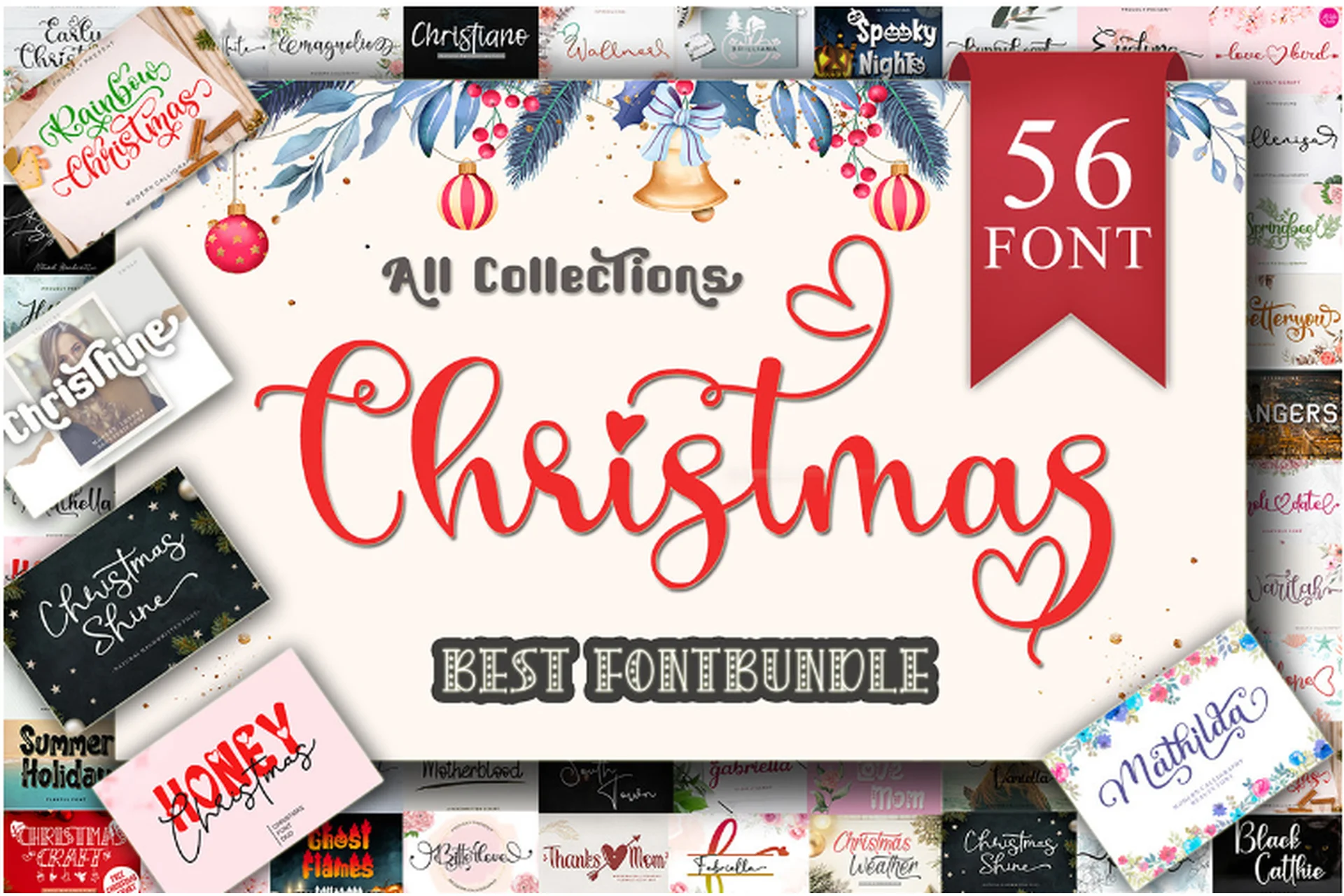
Christmas Font Bundle - это 56 потрясающих шрифтов для ваших праздничных проектов. Потрясающие шрифты, универсальные шрифты для оформления и уникальные декоративные шрифты - этот единственный в своем роде набор станет отличным дополнением к вашей библиотеке шрифтов!